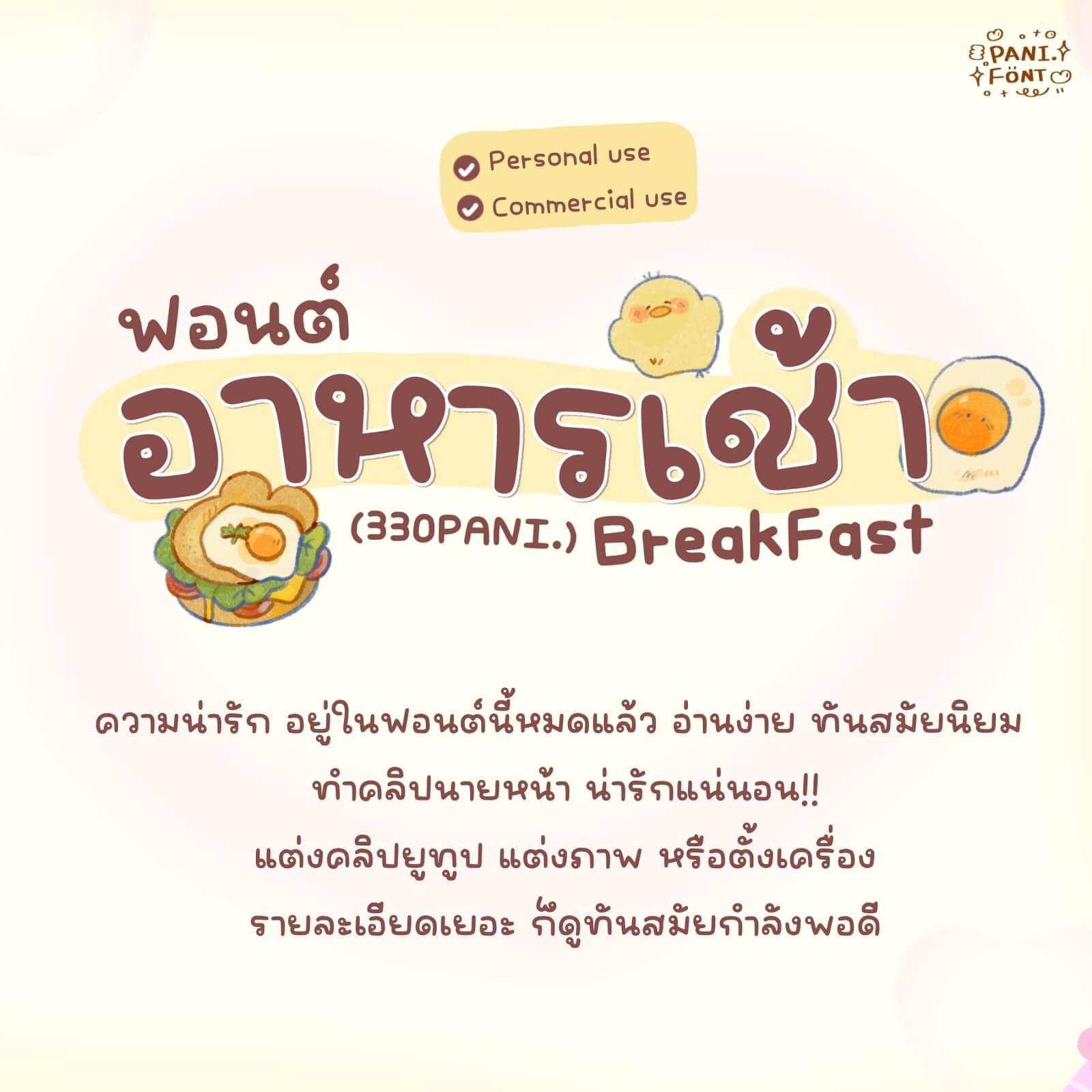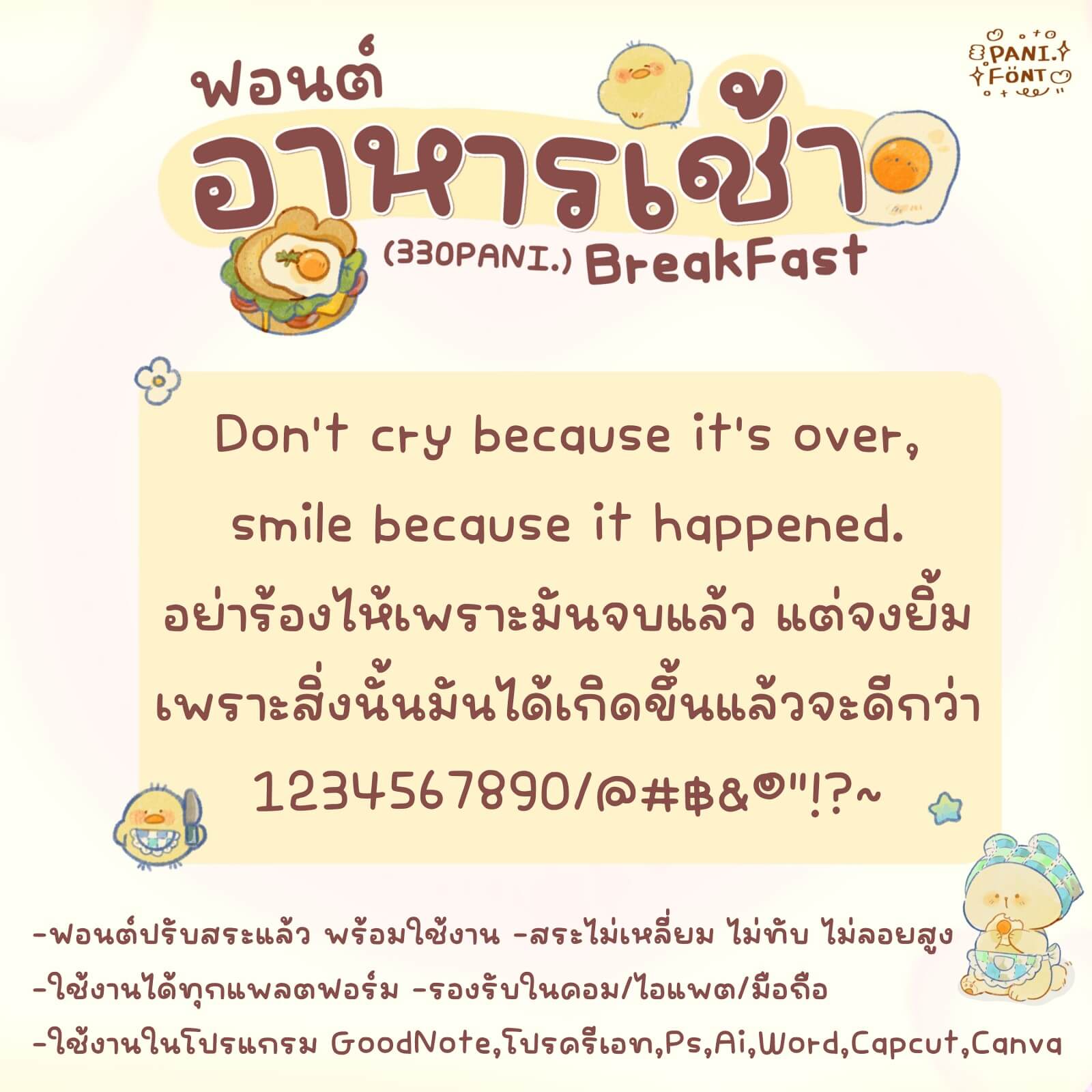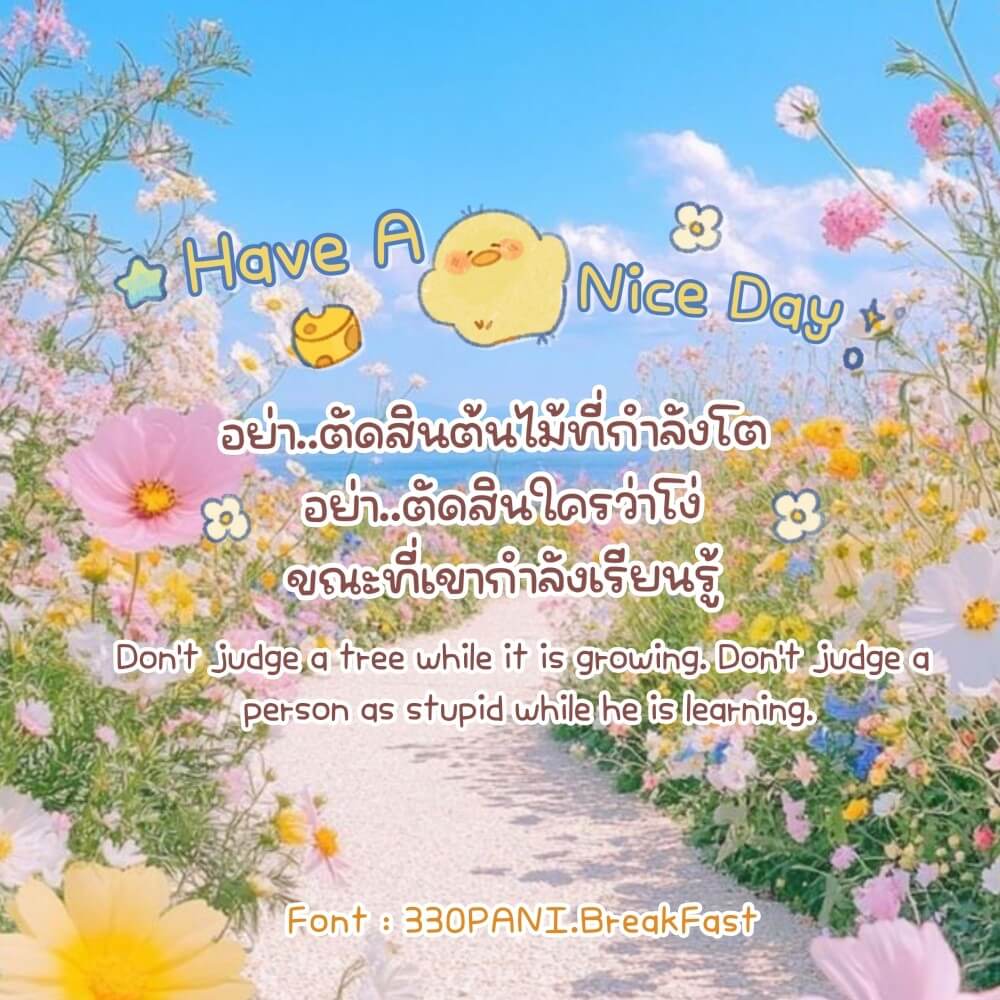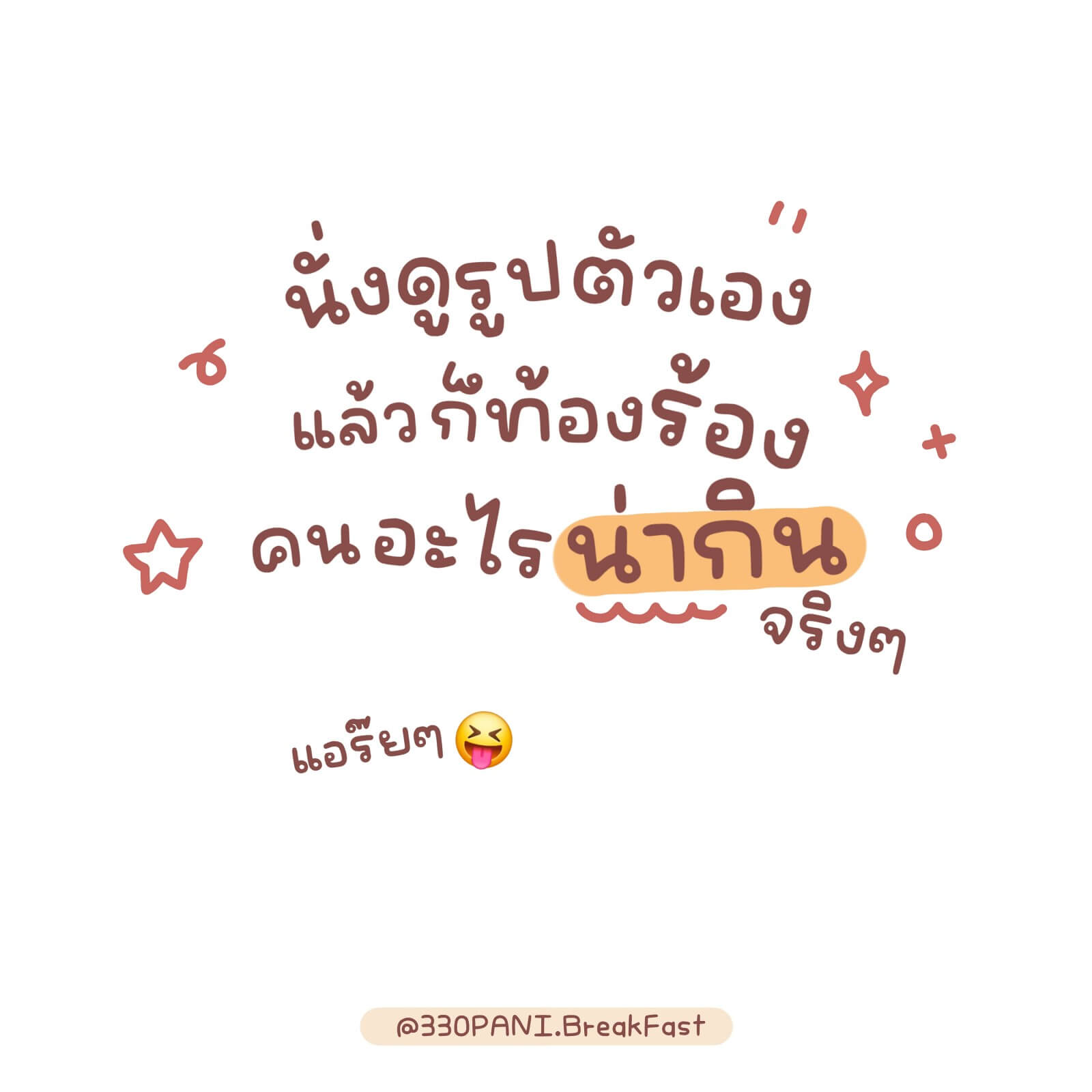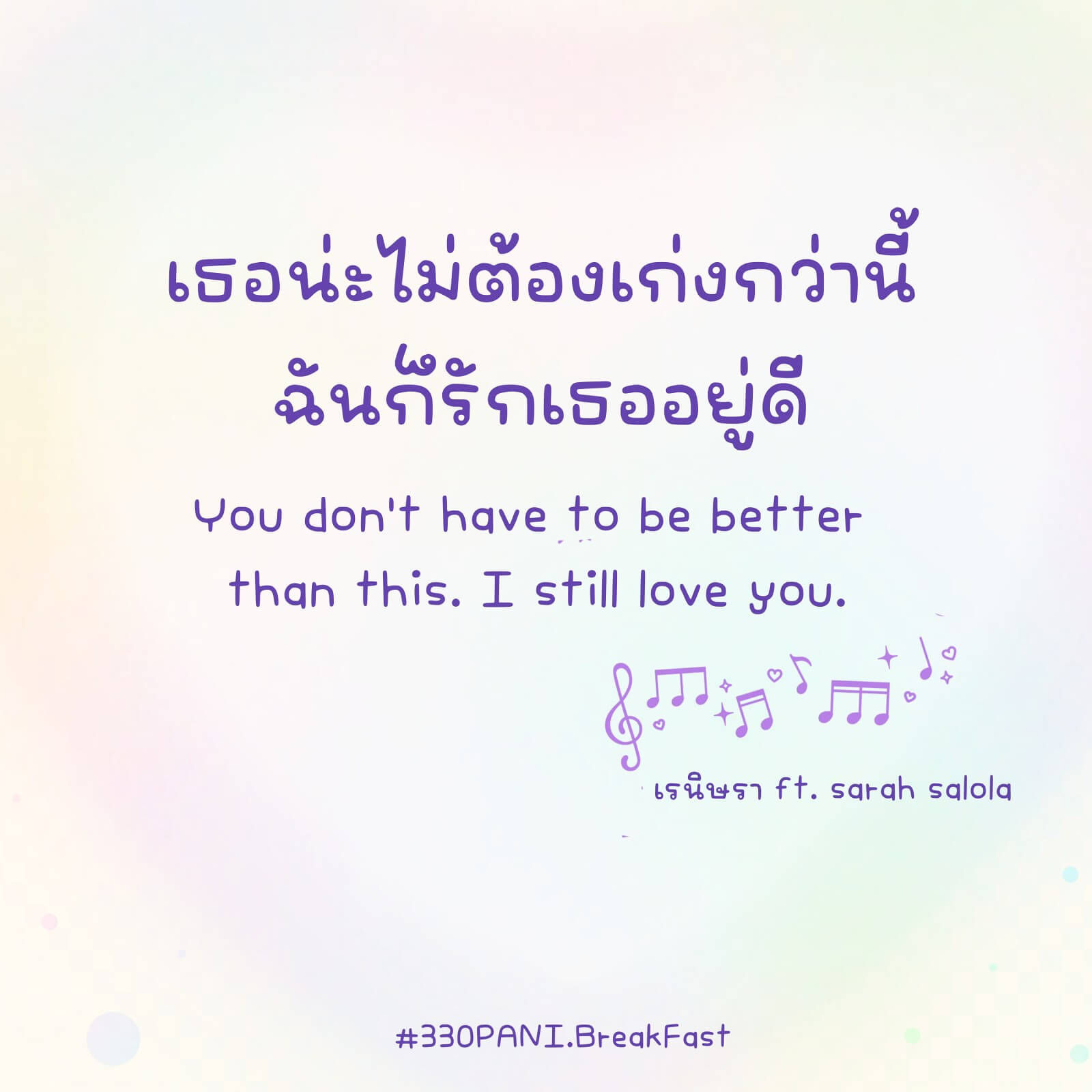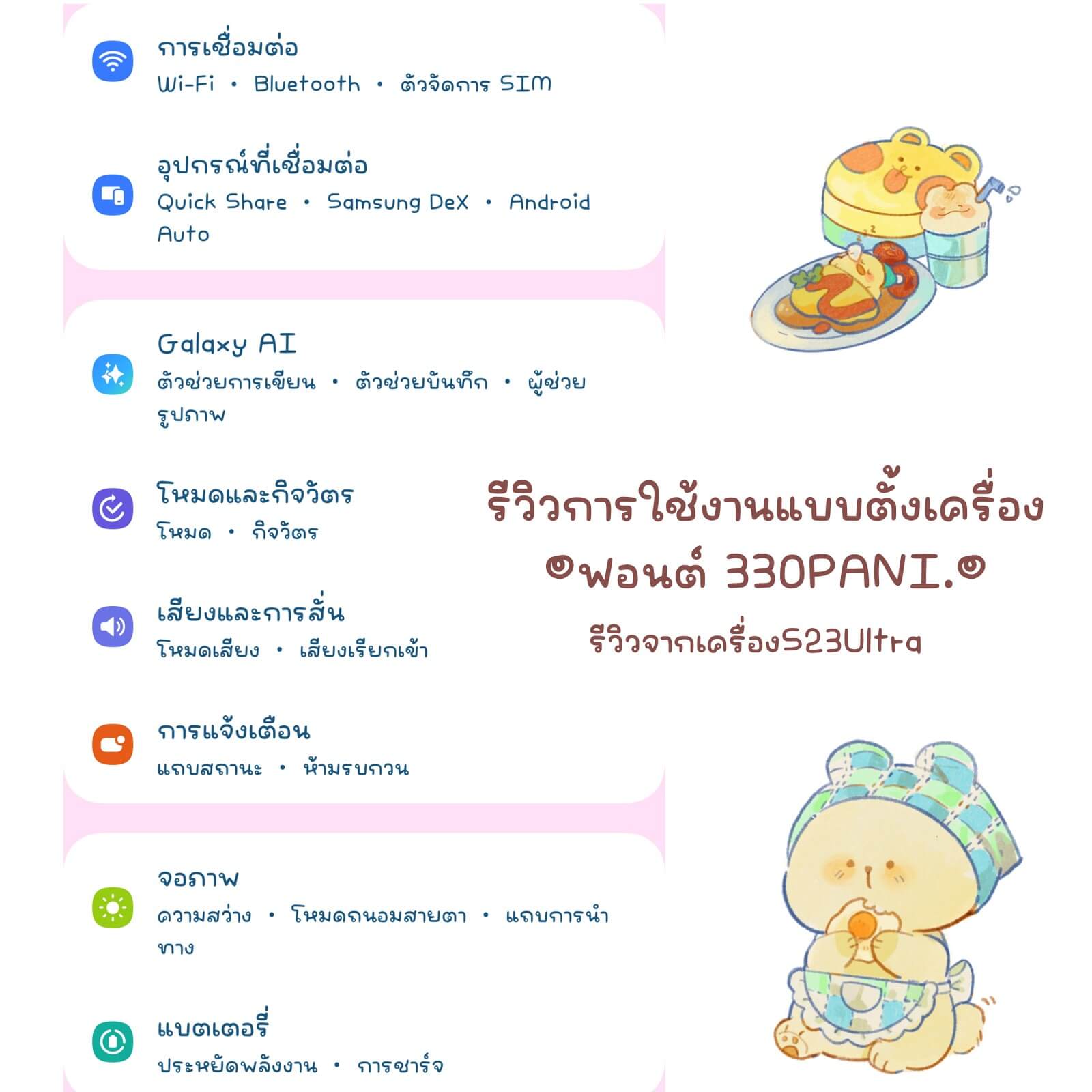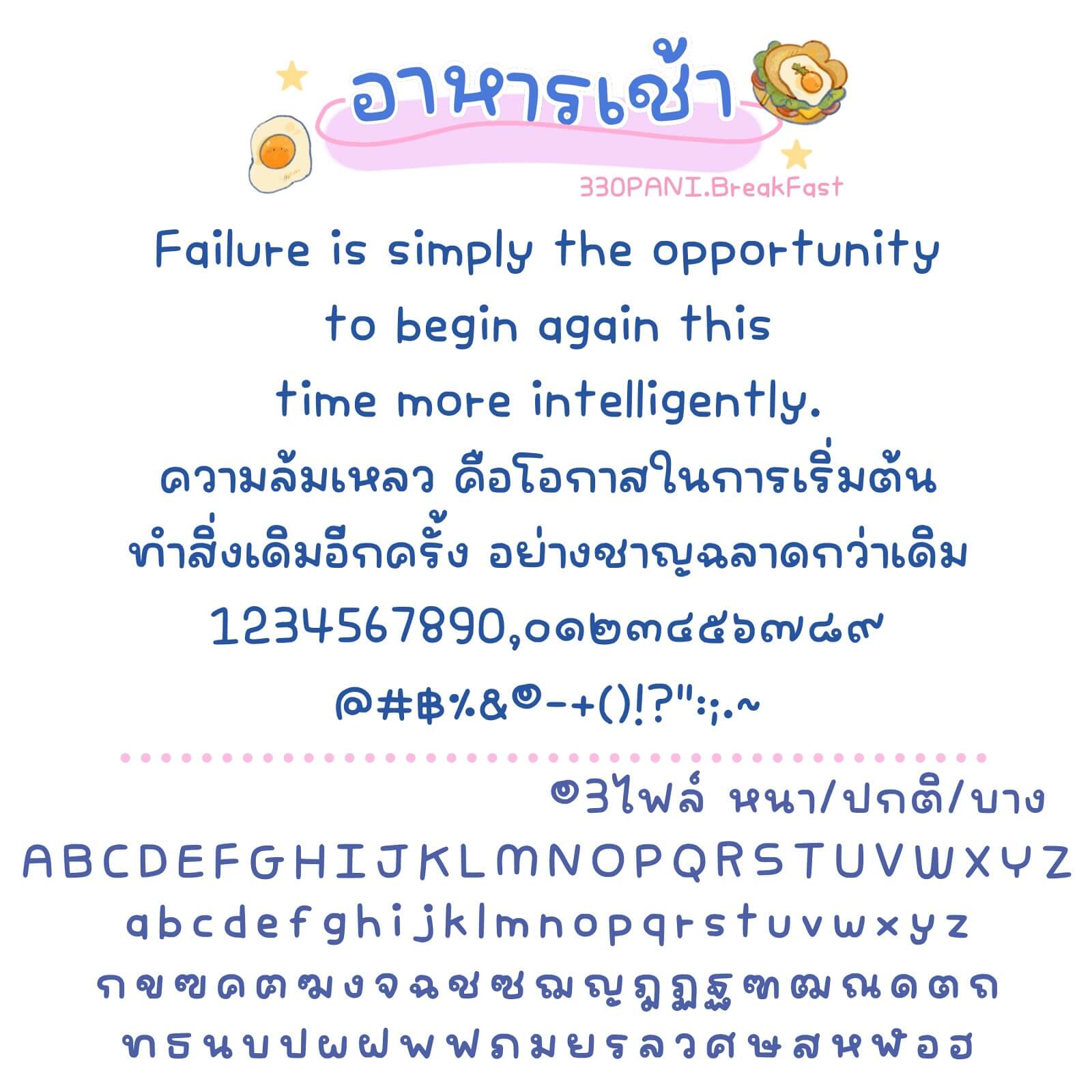
ฟอนต์ 330PANI.BreakFast – โหลดทดลองใช้ฟรีตัว Demo ฟอนต์แนวอ่านง่าย ตัวขนาดกำลังดี ชุดนี้แนะนำเลยค่ะ ใช้งานได้หลากหลายแบบ ใช้กันยาวๆ ได้เลย
330PANI.BreakFast